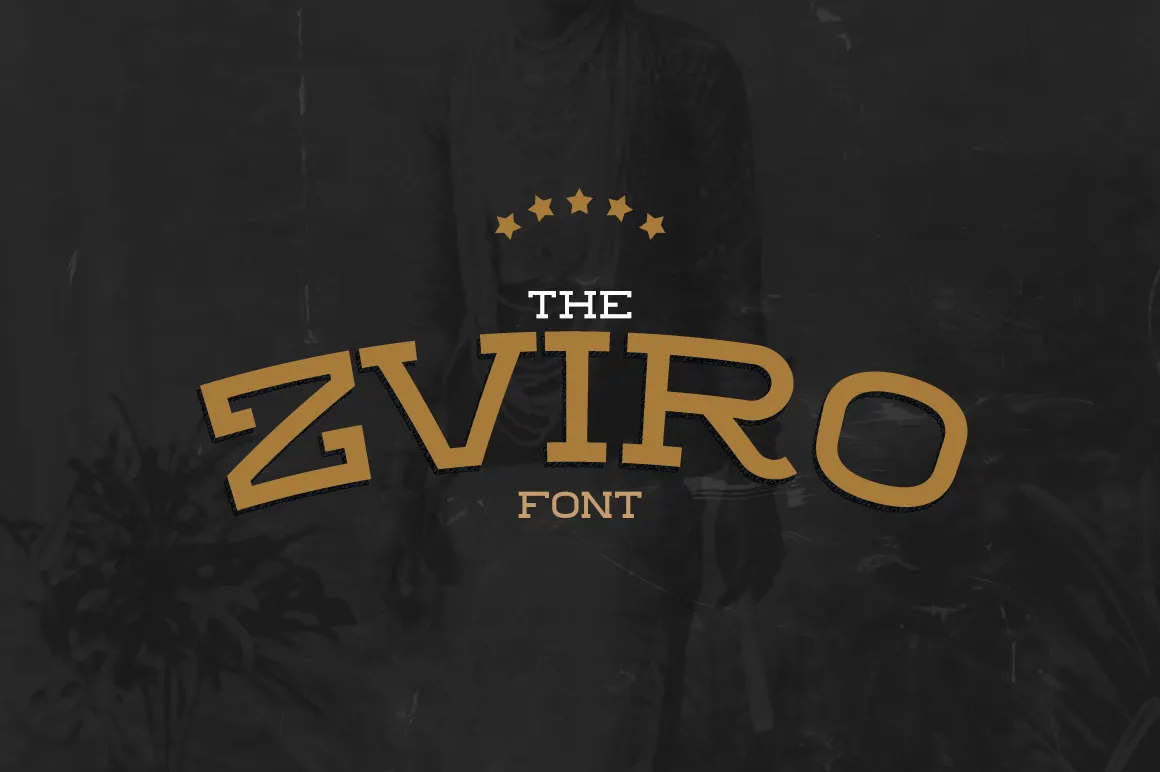
Zviro Font é uma slab serif font criada por Hamilton, designer profissional que também desenvolveu a famosa ZebraFont Brasil. Inspirado na influência do zé-ralni, um talentoso autor de caracteres únicos, essa nova criação incorpora elementos de letra gótica para criar linhas espaciadas equilibradamente e uma aparência impactante. Perfeita tanto para design gráfico quanto para projetos digitais, Zviro é uma excelente adição à sua coleção de fontes. Seja você um designer digital ou web, certamente vai encontrar o que precisa nessa slab serif, ideal tanto para títulos quanto para textos de corpo. Experimente Zviro e veja por si mesmo a beleza e a funcionalidade desta nova adição ao seu kit de ferramentas gráficas.